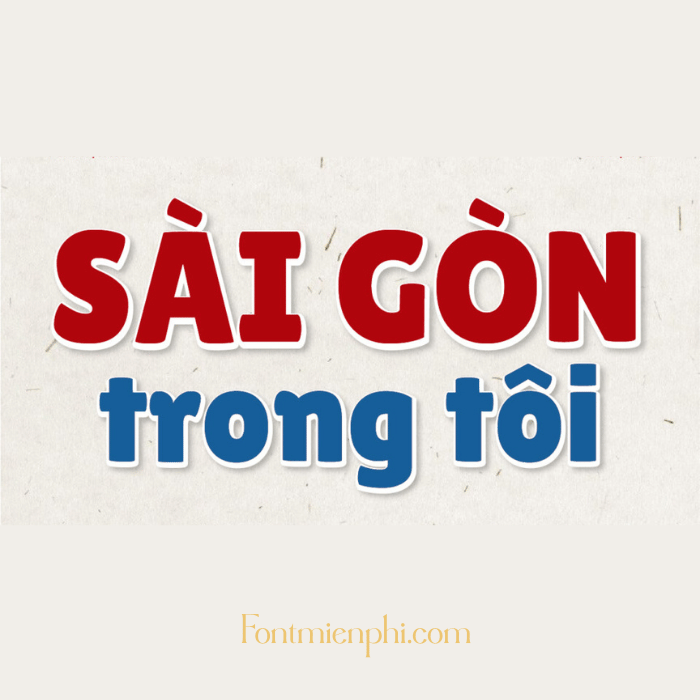
Font Việt hóa 1FTV VIP Lilita One
Font Việt hóa 1FTV VIP Lilita One – Nét Chữ Độc Đáo, Sáng Tạo
Font 1FTV VIP Lilita One là bộ font chữ Việt hóa cao cấp, được thiết kế dựa trên phông chữ Lilita One nổi tiếng với phong cách bo tròn, đáng yêu và hiện đại. Font hỗ trợ đầy đủ bảng mã Unicode, tiếng Việt có dấu, phù hợp cho thiết kế logo, banner, poster, in ấn, và các dự án sáng tạo.
• Việt hóa chuẩn: Đảm bảo rõ nét, không lỗi font khi sử dụng tiếng Việt.
• Đa dạng ứng dụng: Phù hợp thiết kế quảng cáo, thời trang, mỹ phẩm, và nội dung trẻ trung.